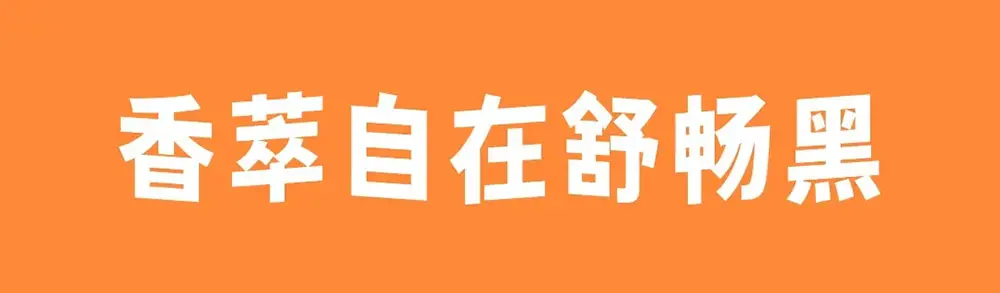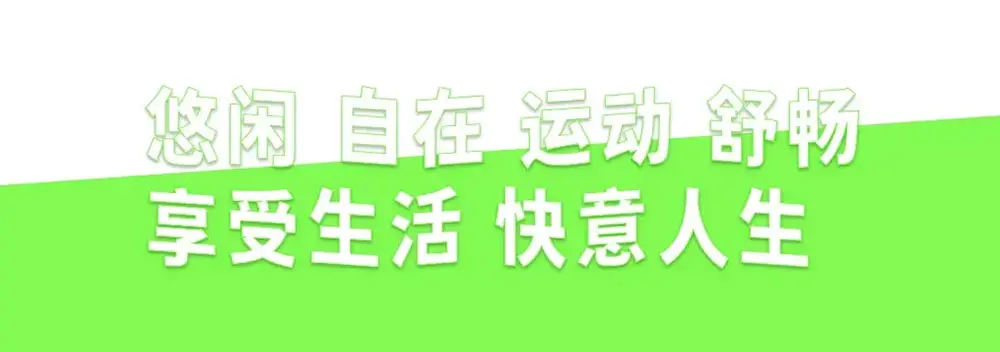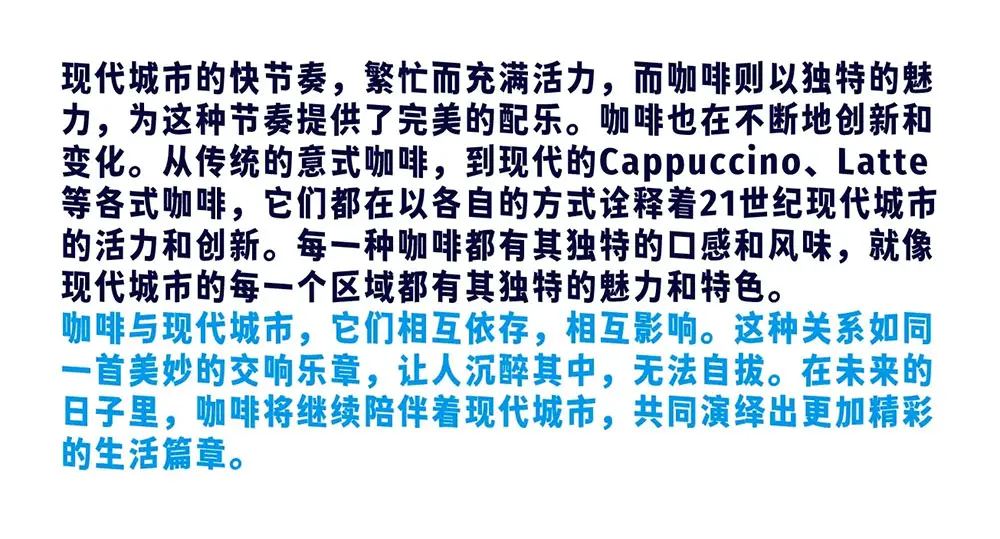
“香萃自在舒暢黑”是一款基於開源字體“未來熒黑”,通過簡單改造而形成的中文字體,支持簡繁漢字。字體呈長方形,多文本排列或長段正文使用時,會形成獨特的波浪效果,極富趣味與動感、清新明快,適用於運動生活、等多種場景,可用於網絡視聽或各類日常商品的包裝設計,允許個人或企業免費商用。未來熒黑是由思源黑體改造而成,但更具簡明、輕快的特徵。未來熒黑剔除了思源黑體原有的喇叭口,和口字部件的豎腳,改變了重心,使其更富有現代化。
漢字作為方塊字形的文字,非常適合構建波浪形,而傳統楷書寫法是縱向略偏長,因此漢字比西文字體更適合做這種改造。添加隨機傾斜效果後的字體,宛如豎立的紙牌,具有立體感;而長段排版時,容易做出層次感。於是這款字體應運而生。事實上,採用折筆更多、曲線更少、字面更大的字體,進行波浪化處理,能呈現更好的效果。但開源字體中,只有思源系列較適合做這類改造。由於現代漢語橫向排版,所以沒有選擇橫向隨機傾斜,而是選擇縱向傾斜,這同時也符合傳統楷書的書寫習慣,即“橫畫斜、豎畫不斜”。